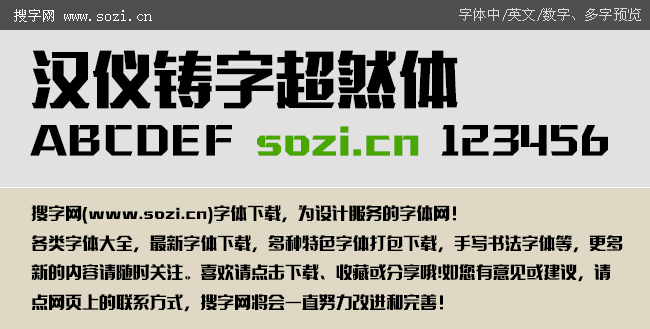
漢儀鑄字超然體
搜字網(wǎng)提供一款漢儀鑄字超然體中文藝術(shù)字體下載,漢儀鑄字超然體是一款漢儀類非主流風(fēng)格字體軟件,超然體筆畫看似雜亂文章,卻透露出非凡的可愛氣息,整體效果十分萌怪,可用于藝術(shù)設(shè)計(jì)、包裝印刷、圖形設(shè)計(jì)等領(lǐng)域。